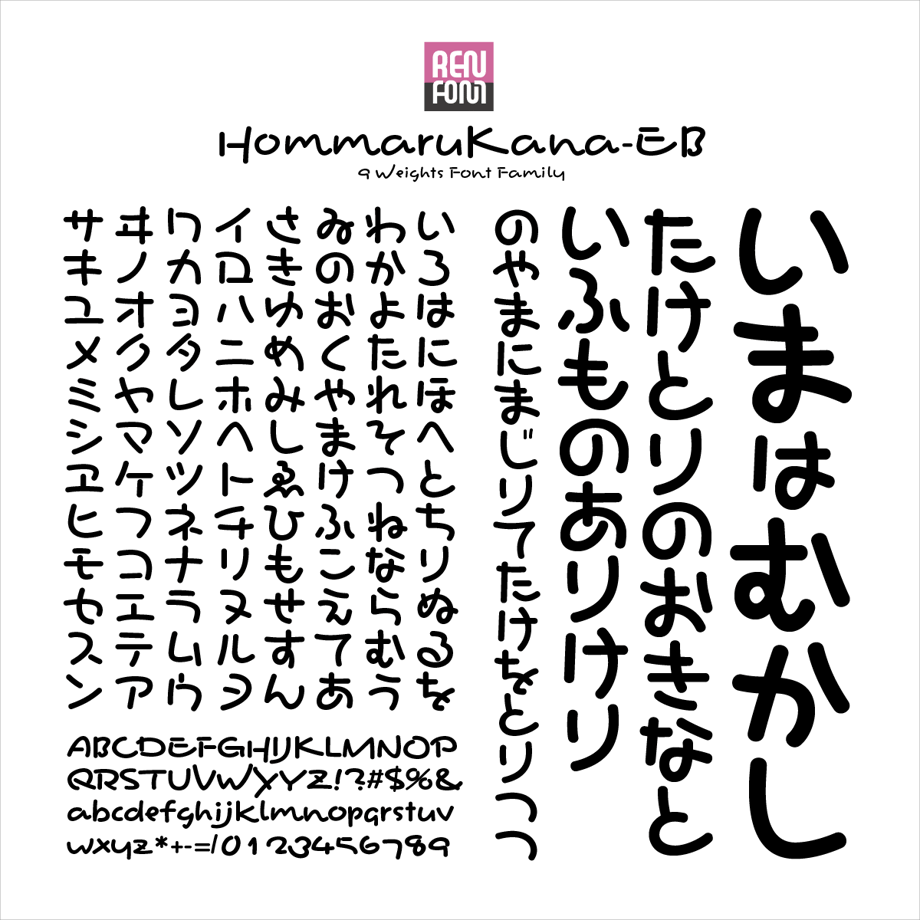
おとなの味な丸もじ ほんまるかな 9ウェイトファミリー / OpenType ■概要 かすかに筆文字の名残り、味わいのある丸もじ。 やや左上に重心がある独特のフォルム。その危うさゆえに不思議なリズムを持っています。 丸ゴシックはもともとPOP寄りの柔らかなたたずまいをしており、デザイン書体との相性がよい書体。「ほんまる」は既存の他社丸ゴシックと組み合わせても違和感なく溶け込み、あたたかな雰囲気を醸し出します。 デザイン書体のかな文字はおしなべて形状が極端なので、普通のベタ組みではバランスがとりにくい傾向があります。「ほんまる」も例外ではありません。 そこで「ほんまる」は、縦組み・横組みのすべての文字にペアカーニングをほどこしました。ですので、メトリクス処理をするだけで、バランスのとれた組みが得られます。 ■ウェイト ●ALL[フルウェイト] ●EL[エクストラライト] ●L[ライト] ●R[レギュラー] ●M[ミディアム] ●DB[デミボールド] ●B[ボールド] ●EB[エクストラボールド] ●H[ヘビー] ●U[ウルトラ] ■特長 ●両仮名 一般的な丸文字とは異なり、かすかに筆文字の名残りを感じる、味わいのあるフォルムに仕上げました。キャッチフレーズ「おとなの味な丸もじ」はそこからきています。 漢字で書くと「奔丸」。既存の行書書体「奔行」の流れを汲んでいます。 重心を左上に置いているため不安定で、リズミカルに踊っているような動きのある楽しい印象を与えます。 丸ゴシックの宿命として硬い内容の文章には不向きですが、「ほんまる」は動的要素が強いので、カジュアルなものに訴求力を発揮します。 ●欧文・数字 従属欧文は当社の場合、比較的オーソドックスなものにしていますが、「ほんまるかな」はスクリプト体です。 跳ねる文字もあれば跳ねずに止まる文字もあり、破天荒でバラエティに富んだ、リズムあふれる書体になっています。使っているだけでウキウキしてくる、無条件で楽しい書体です。 ■収録文字 796文字 この書体は、すべてのフォントフォーマットにおいて、Adobe-Japan1-3 に準拠し制作されています。含まれる文字種は以下の通りです。 ●仮名 ・平仮名(全角全文字) ・片仮名(全角全文字) ●欧文 ・プロポーショナル欧文 98文字 ・90度時計回り回転プロポーショナル欧文 98文字 ・全角欧文 98文字 ●記号類 ・常用する句読点類・約物類のみ ●罫線類 ・罫線素片類(全角・半角) ■動作環境 Mac ●ハードウェア / MacOSX 10.0.0 以降 macOS 10.15までの各バージョンのいずれかがストレスなく動作する Macintosh ●ハードディスク容量 / 1ウェイト毎に4MBのハードディスクスペース ※OpenTypeは、将来的にOSのバージョンが上がっても継続してご利用いただけます。 ※技術的には ATM をインストールした MacOS 8.6〜9.2.2、MacOS X 10.0〜10.9 で表示・印刷は可能ですが、Apple 社のサポートサイクルに則り、サポート対象とはしておりません。